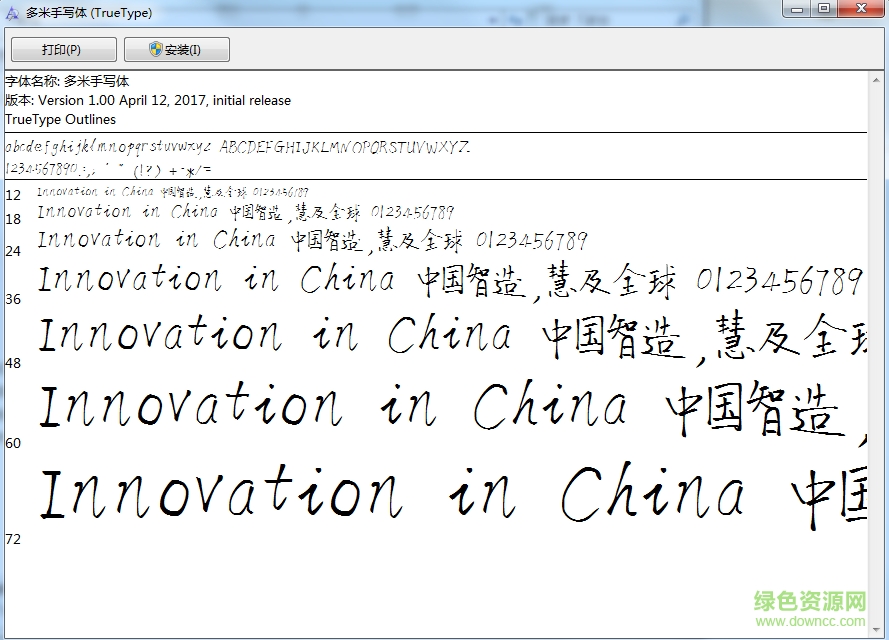
多米手寫(xiě)體是一款個(gè)性十足、清秀簡(jiǎn)約的書(shū)法字體,以鋼筆書(shū)法為綱、以自由肆意為髓,適合海報(bào)印刷、名片設(shè)計(jì)等場(chǎng)合,歡迎大家免費(fèi)下載!
多米手寫(xiě)體是一款用于手寫(xiě)設(shè)計(jì)方面的藝術(shù)字體,支持繁簡(jiǎn)體輸入,字跡流暢溫和、活潑中透著嚴(yán)謹(jǐn)之風(fēng),可用于多種設(shè)計(jì)創(chuàng)意場(chǎng)合。